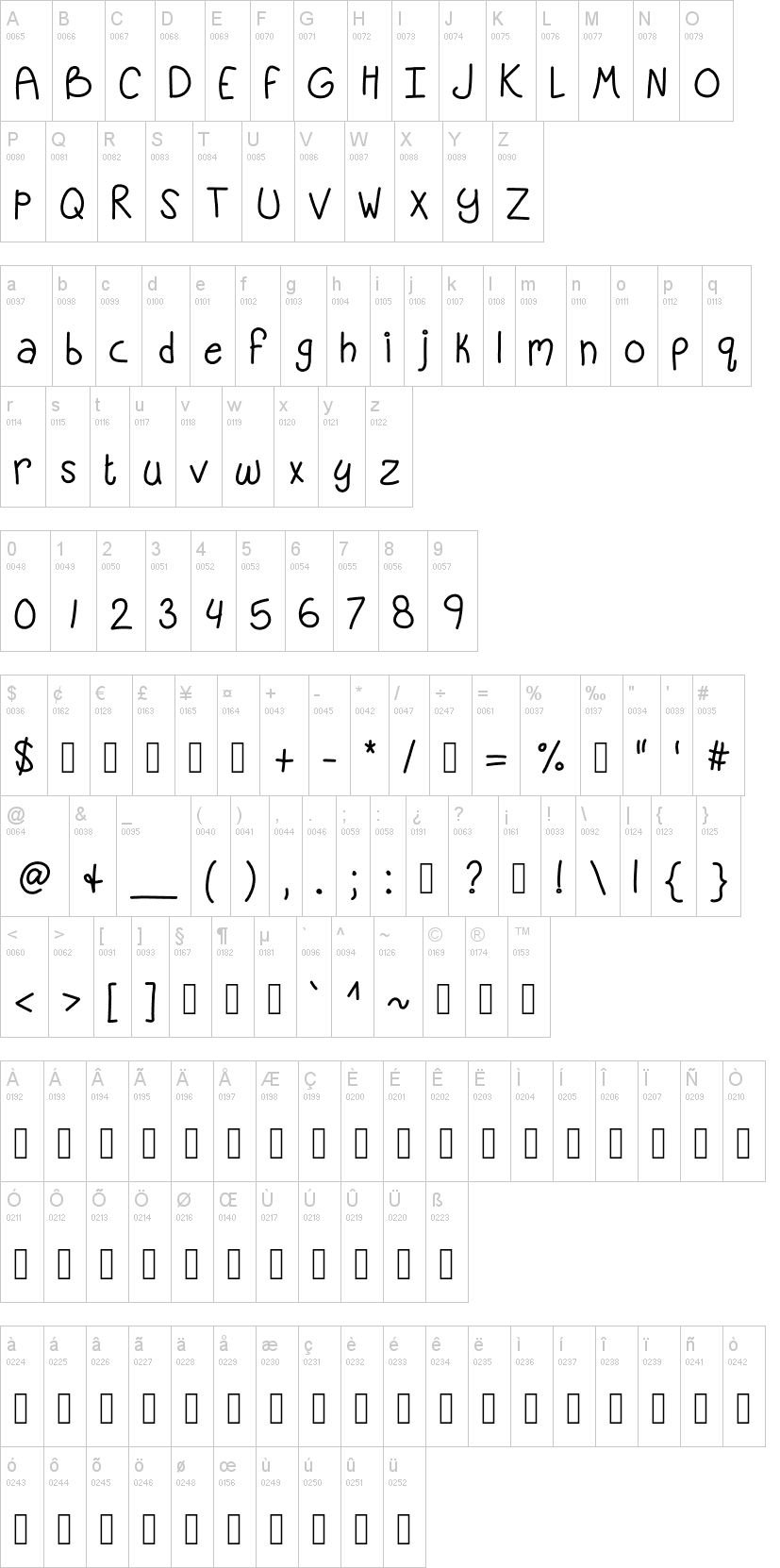
KB Sandy Shorts
? KB Sandy Shorts 是一款活泼可爱的字体,它拥有简单的线条和曲线,可以创造出活泼可爱的感觉,并且具有较强的抽象性,可以搭配出不同的设计风格。它有着多种不同的字体风格,可以满足不同的设计需求,是一款非常有趣的字体。
KB Sandy Shorts是一款非常不错的手写艺术字体,具有很好的视觉感,适合于文化类的宣传设计、商业类品牌的广告和产品包装设计以及个性化文字排版等较多场景。
KB Sandy Shorts字符映射图